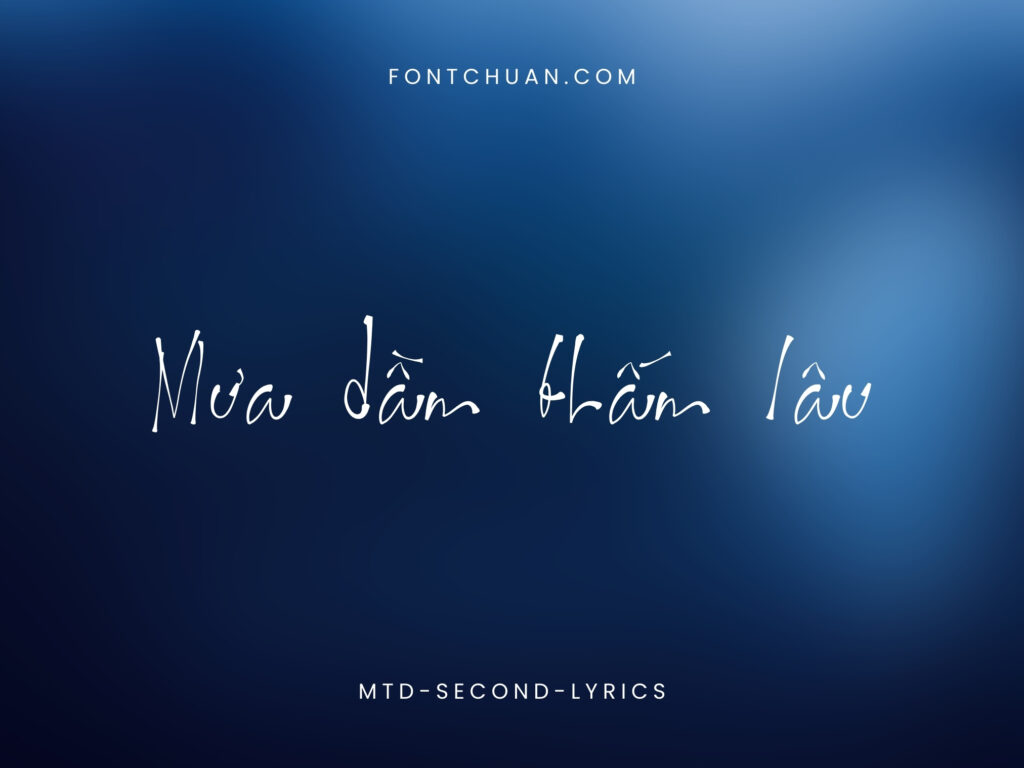
Font MTD Second Lyrics Việt Hóa
Tác giả Font: Mans Greback
Font MTD Second Lyrics là một phông chữ script viết tay độc đáo, được thiết kế với các đường nét mềm mại và uyển chuyển, mang đến cảm giác tự nhiên và thân thiện. Font đã được Việt hóa bởi Mộc Hạ, hỗ trợ tiếng Việt và hơn 90 ngôn ngữ khác, giúp mở rộng khả năng ứng dụng trong các thiết kế đa ngôn ngữ. Đây là một trong những phông chữ được cộng đồng thiết kế đánh giá cao và ứng dụng trong nhiều dự án sáng tạo, đáp ứng nhu cầu đa dạng của người dùng.
MTD Second Lyrics nổi bật với thiết kế tinh tế, phù hợp cho các dự án yêu cầu sự sáng tạo và cá nhân hóa. Font rất phù hợp cho các thiết kế logo, tiêu đề, bao bì sản phẩm, thiệp mời và các ấn phẩm đòi hỏi sự tinh tế và nghệ thuật. Các ngành nghề phù hợp bao gồm quảng cáo, giáo dục, công nghệ, thiệp cưới và ảnh cưới. Font này cũng lý tưởng cho các sự kiện như Tết, Giáng sinh, Valentine và các lễ hội khác.